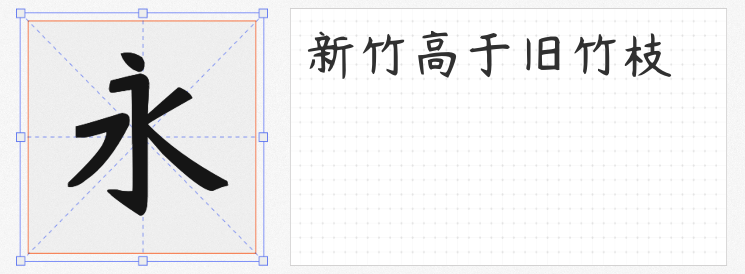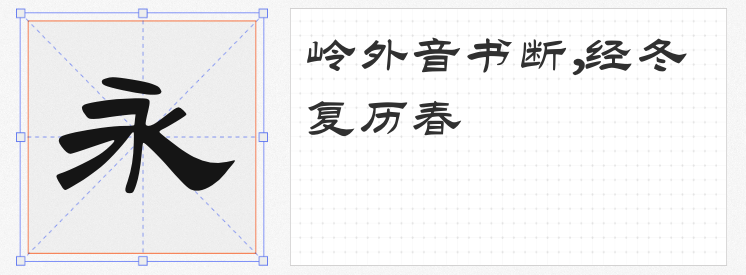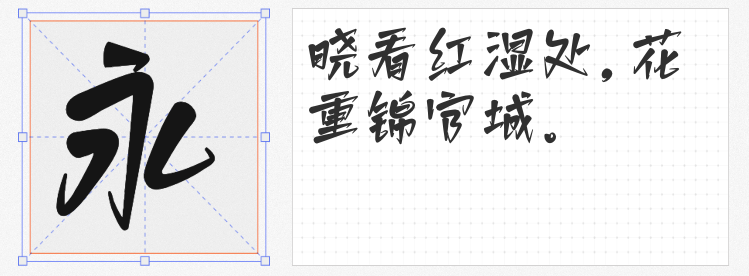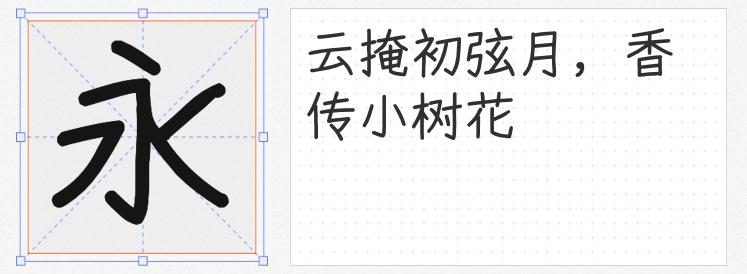
当第一片梧桐叶飘落,立秋的画卷徐徐展开。这个充满诗意与丰收寓意的节气,在设计中需要既能承载文化底蕴又兼具视觉美感的字体。本文精选四款免费商用字体,从手写温度到历史厚重感,为节气主题设计提供多元选择。
1. 悠哉字体 中等
基于Y.OzFont改造的悠哉字体,以自然拼接的笔触还原真实书写质感。略带倾斜的笔画与不规则的收尾,恰似秋风掠过纸面的灵动。在立秋海报中,这款字体能完美呈现"一叶知秋"的意境,尤其适合搭配水墨背景或手绘插画,营造返璞归真的节气氛围。
2. 杨任东竹石体-Medium
覆盖7311个字符的杨任东竹石体,以刚劲笔锋诠释"立秋三候"的坚韧。这款源自GB2312标准的字体,在保持传统书法结构的同时,通过适度的现代化调整,让"寒蝉鸣""白露降"等节气物语更具视觉张力。其横细竖粗的对比处理,尤其适合需要突出文化厚重感的标题设计。
3. 白路棒棒手写体
包含6796个字符的白路棒棒手写体,用圆润的笔画勾勒出立秋的温柔。数字与英文的统一设计,让节气文案的排版更具呼吸感。这款字体在社交媒体海报中表现尤为出色,当"贴秋膘""咬秋瓜"等民俗文字以这种略带稚拙的笔触呈现时,瞬间唤醒年轻人对传统文化的亲近感。
4. 鼎猎客家体
源自魏晋爨体的客家专属字体,以拙朴字形重构立秋的仪式感。鼎猎客家体将客家围屋的建筑美学融入笔画,在"晒秋""秋祭"等主题设计中,其独特的楔形结构与飞白效果,能瞬间提升画面的历史纵深感。这款字体特别适合文旅宣传或非遗主题的节气物料制作。
从手写温度到历史回响,这四款字体以不同维度诠释着立秋的文化密码。设计师可根据具体场景需求,选择最能传递节气精神的表达方式,让每个文字都成为连接传统与现代的视觉。